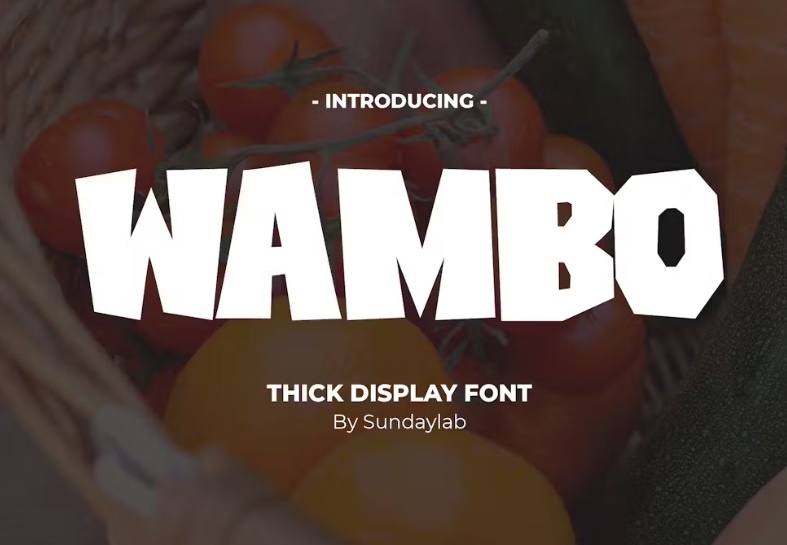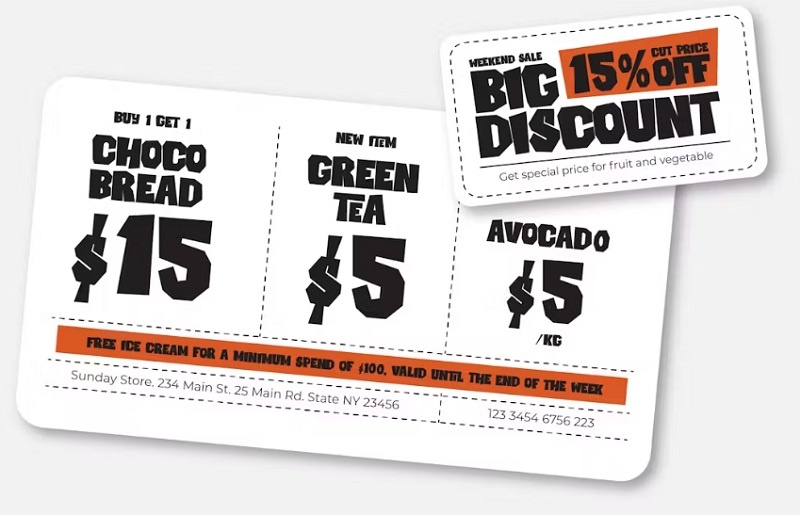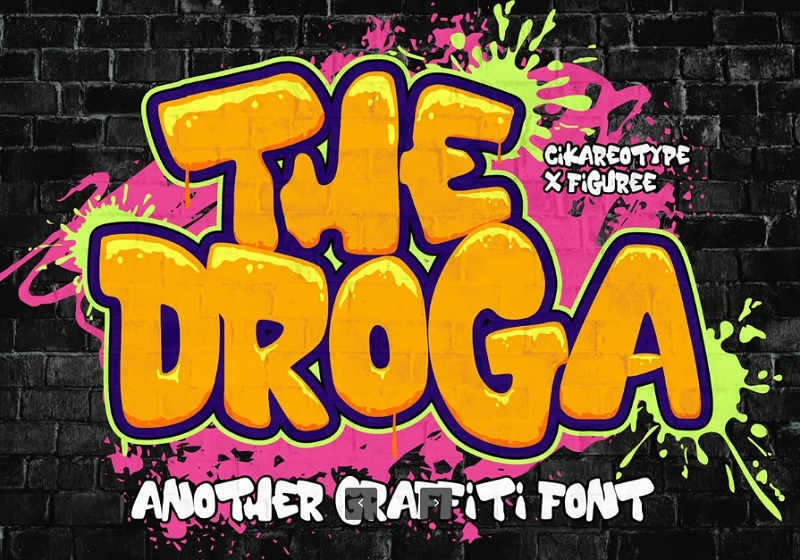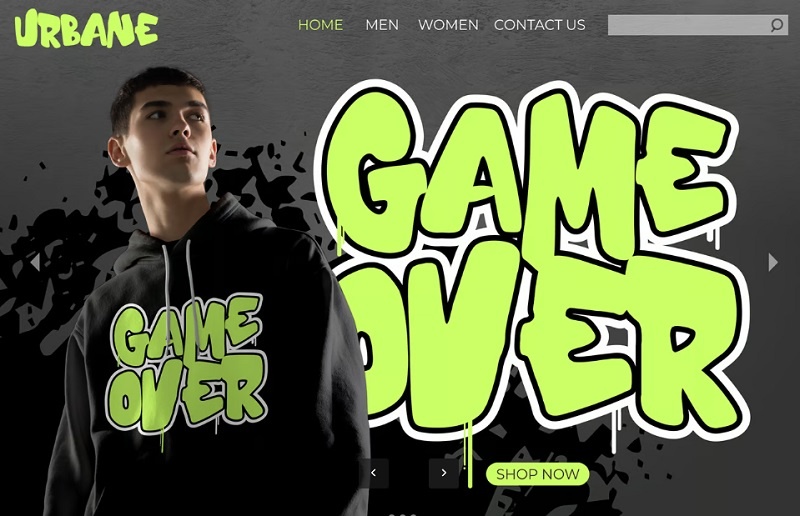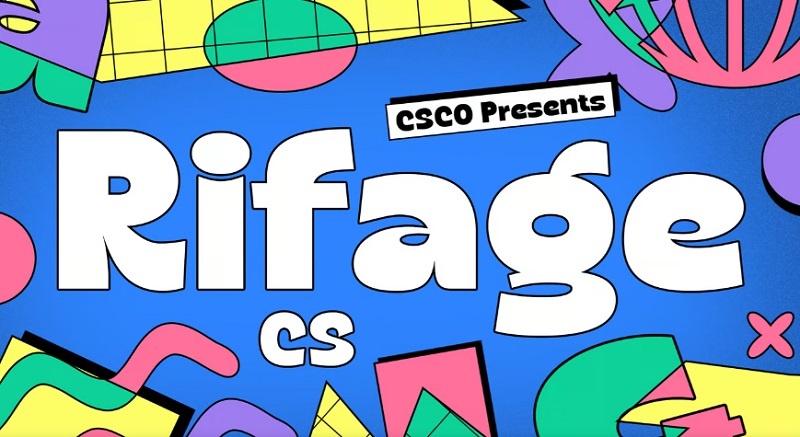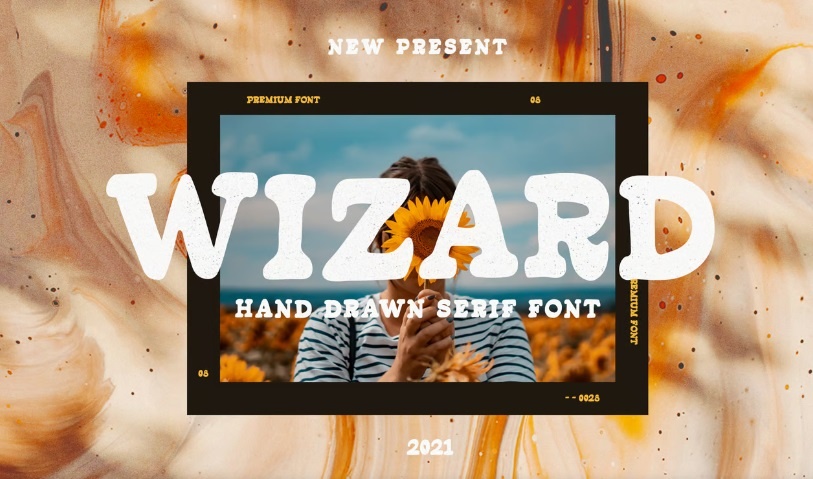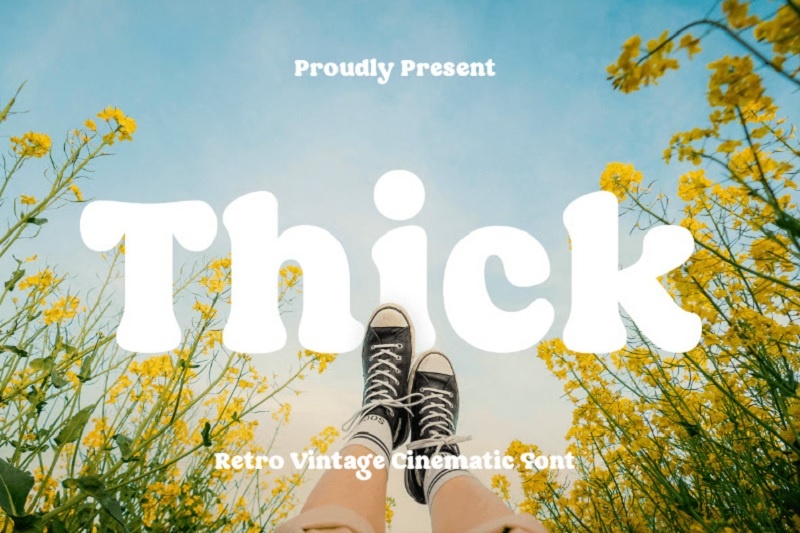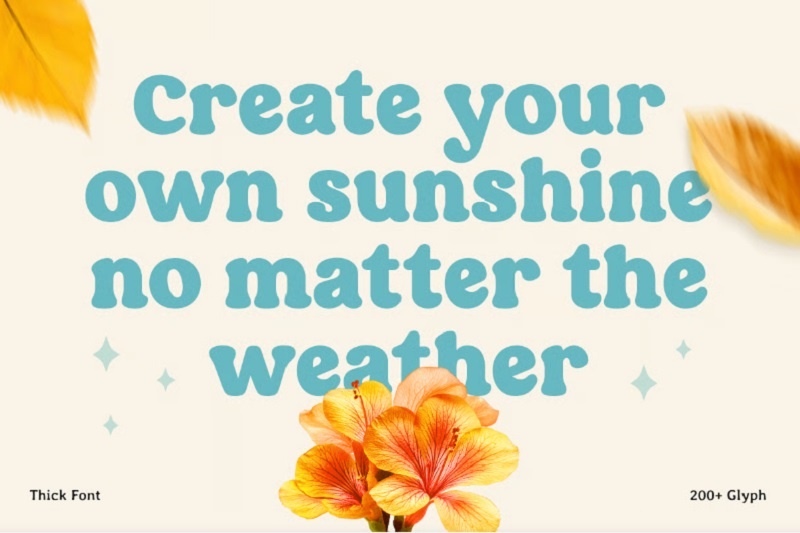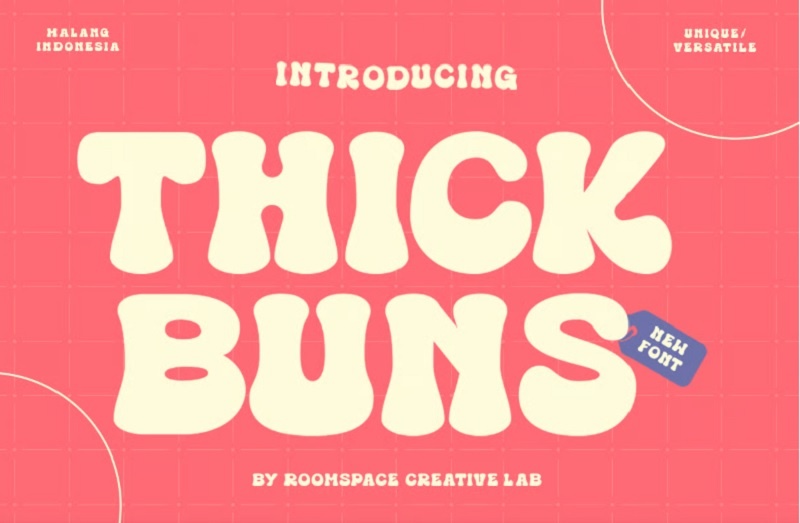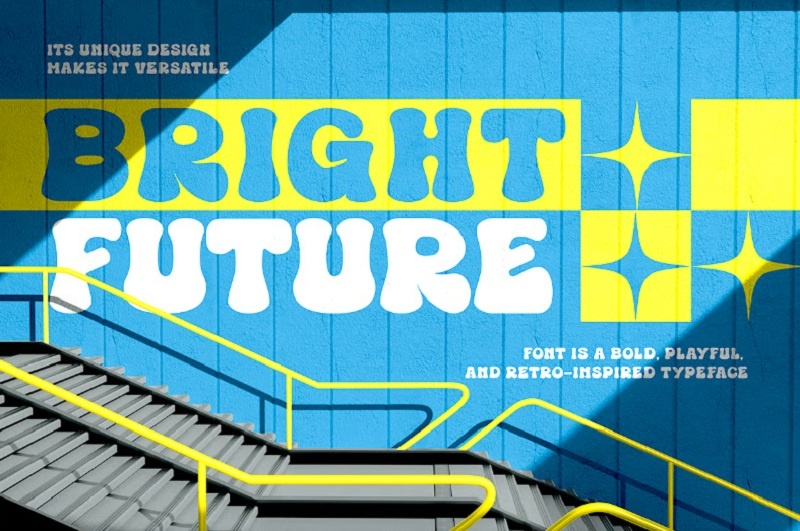
8 فونت ضخیم انگلیسی Battom Glory
فونت ضخیم انگلیسی Battom Glory
فونت ضخیم انگلیسی Battom Glory شامل مجموعه فونت های بولد و برجسته است. این فونت دارای طراحی منحصر به فرد و درجه یک است که آن را برای نیازهای طراحی فوق العاده شما عالی می کند. این فونت را برای طراحی ایده های خلاقانه خود اضافه کنید و ببینید که چگونه آن را متمایز می کند! برای دانلود و مشاهده تصاویر این فونت انگلیسی زیبا در ادامه از سایت gfx با ما همراه باشید.
فونت بولد انگلیسی Battom Glory
فونت انگلیسی ضخیم Battom Glory
دانلود فونت انگلیسی ضخیم Battom Glory
فونت ضخیم Battom Glory
فونت ضخیم انگلیسی
دانلود فونت ضخیم انگلیسی
Wambo Thick نام این فونت انگلیسی ضخیم و برجسته است. این فونت ضخیم انگلیسی مناسب برای تایتل ها، برچسب ها، عناوین ها و سایر رسانه های تبلیغاتی مناسب است.
فونت انگلیسی ضخیم  و پر رنگ
فونت های ضخیم انگلیسی
Droga یک فونت ضخیم انگلیسی با سبک گرافیتی است. مناسب برای برندسازی، سرفصل‌ها، طرح‌های عروسی، دعوت‌نامه‌ها، امضاها، لوگوتایپ‌، تصاویر هنر دیواری، لیبل و موارد دیگر می باشد. شامل فایل های OTF، TTF و WOFF است.
دانلود فونت های ضخیم انگلیسی
فونت پهن انگلیسی مناسب برای طراحی پوستر و بنر
بهترین فونت‌های پهن و ضخیم انگلیسی برای عنوان‌نویسی
اگر به دنبال یک فونت ضخیم و پهن انگلیسی قدرتمند و جذاب برای طراحی‌های گرافیکی یا پروژه‌های تبلیغاتی خود هستید، استفاده از این فونت های ضخیم انگلیسی می‌تواند انتخابی خلاقانه و تاثیرگذار باشد. این نوع فونت‌ها با ساختار پهن و برجسته‌ای که دارند، توجه بیننده را به سرعت جلب می‌کنند و برای عنوان‌نویسی، طراحی پوستر، کاور و بنرهای تبلیغاتی بسیار کاربردی‌اند. در این مطلب، مجموعه‌ای منتخب از فونت پهن انگلیسی را برای شما آماده کرده‌ایم که می‌توانید با یک کلیک، دانلود فونت ضخیم انگلیسی را انجام دهید و از آن‌ها در پروژه‌های شخصی یا حرفه‌ای خود بهره ببرید.
دانلود برترین فونت‌های Bold انگلیسی برای طراحان
فونت‌های بولد انگلیسی در طراحی گرافیک و تبلیغات
فونت‌ های ضخیم انگلیسی برای طراحی گرافیک و تبلیغات
اگر به دنبال فونت انگلیسی درشت و ضخیم هستید تا در طراحی پوستر، بنر یا کاورهای حرفه‌ ای جلوه‌ی متفاوتی ایجاد کنید، پیشنهاد می‌ کنیم مجموعه‌ ای از بهترین فونت‌ ضخیم بولد را امتحان کنید. استفاده از این سبک فونت باعث جلب توجه بیشتر متن می‌ شود و خوانایی بالاتری برای مخاطب دارد. در این مطلب می‌ توانید به‌راحتی دانلود فونت ضخیم انگلیسی برای ادیت و طراحی را انجام دهید و از آن در نرم‌ افزارهای محبوبی مثل فتوشاپ، ایلاستریتور و حتی در طراحی سایت بهره ببرید. این فونت‌ ها برای عنوان‌های برجسته، لوگوتایپ و پروژه‌ های گرافیکی حرفه‌ای انتخابی ایده‌آل هستند.
فونت‌ های ضخیم انگلیسی برای تایپوگرافی
دانلود فونت کلفت انگلیسی مخصوص فتوشاپ و طراحی بنر
دانلود فونت کلفت و پهن انگلیسی مخصوص فتوشاپ و طراحی بنر
اگر به دنبال طراحی حرفه‌ ای و چشم‌ گیر هستید، استفاده از فونت پهن انگلیسی یکی از بهترین انتخاب‌ ها برای ساخت بنر، پوستر یا کاور است. این نوع فونت‌ ها با ساختار کلفت و برجسته خود، جلوه‌ ای مدرن و قدرتمند به طرح می‌ دهند. طراحان گرافیک معمولاً از فونت کلفت انگلیسی در پروژه‌ هایی استفاده می‌ کنند که نیاز به جلب توجه یا تأکید بر متن دارند. در این صفحه می‌ توانید دانلود فونت انگلیسی ضخیم برای فتوشاپ را انجام دهید و در پروژه‌های تبلیغاتی یا طراحی لوگو از آن بهره ببرید.
دانلود فونت انگلیسی ضخیم برای فتوشاپ
فونت انگلیسی ضخیم مناسب لوگو، پوستر و طراحی گرافیک
دانلود فونت انگلیسی ضخیم و درشت برای لوگو و برندینگ
اگر به دنبال فونت انگلیسی ضخیم و درشت برای طراحی حرفه‌ ای هستید، انتخاب یک فونت درشت مناسب می‌ تواند تاثیر زیادی روی جذابیت بصری پروژه شما داشته باشد. دانلود فونت ضخیم انگلیسی Tighton برای لوگو، نیاز طراحان گرافیک، طراحان لوگو و تولیدکنندگان محتوا رو برطرف خواهد کرد. این نوع فونت‌ در طراحی لوگو، پوستر، بنر تبلیغاتی، کاور اینستاگرام و طراحی برندینگ کاربرد فراوانی دارد. در این مطلب می‌ توانید مجموعه‌ ای از بهترین فونت‌ های انگلیسی پهن و درشت را با کیفیت بالا دانلود کرده و در پروژه‌ های گرافیکی و تبلیغاتی خود استفاده کنید.
دانلود فونت بولد انگلیسی حرفه‌ای برای برندینگ
✅ نام فونت انگلیسی 1: Battom Glory
✅ نام فونت انگلیسی 2: Wambo Thick
✅ نام فونت انگلیسی 3: The Droga
✅ نام فونت انگلیسی 4: CS Rifage – Bold Font
✅ نام فونت انگلیسی 5: WIZARD BOLD
✅ نام فونت انگلیسی 6: Thick - Retro Vintage
✅ نام فونت انگلیسی 7: Thick Buns
✅ نام فونت انگلیسی 8: Tighton Condensed Font